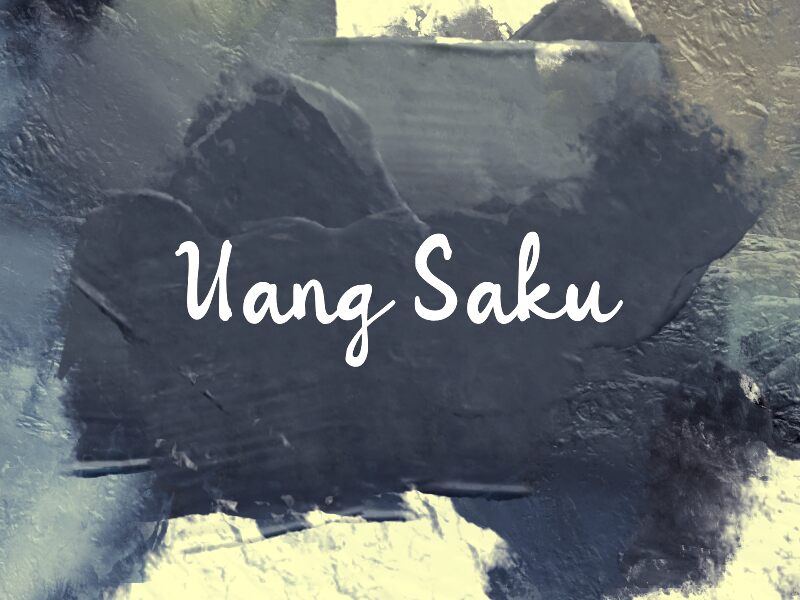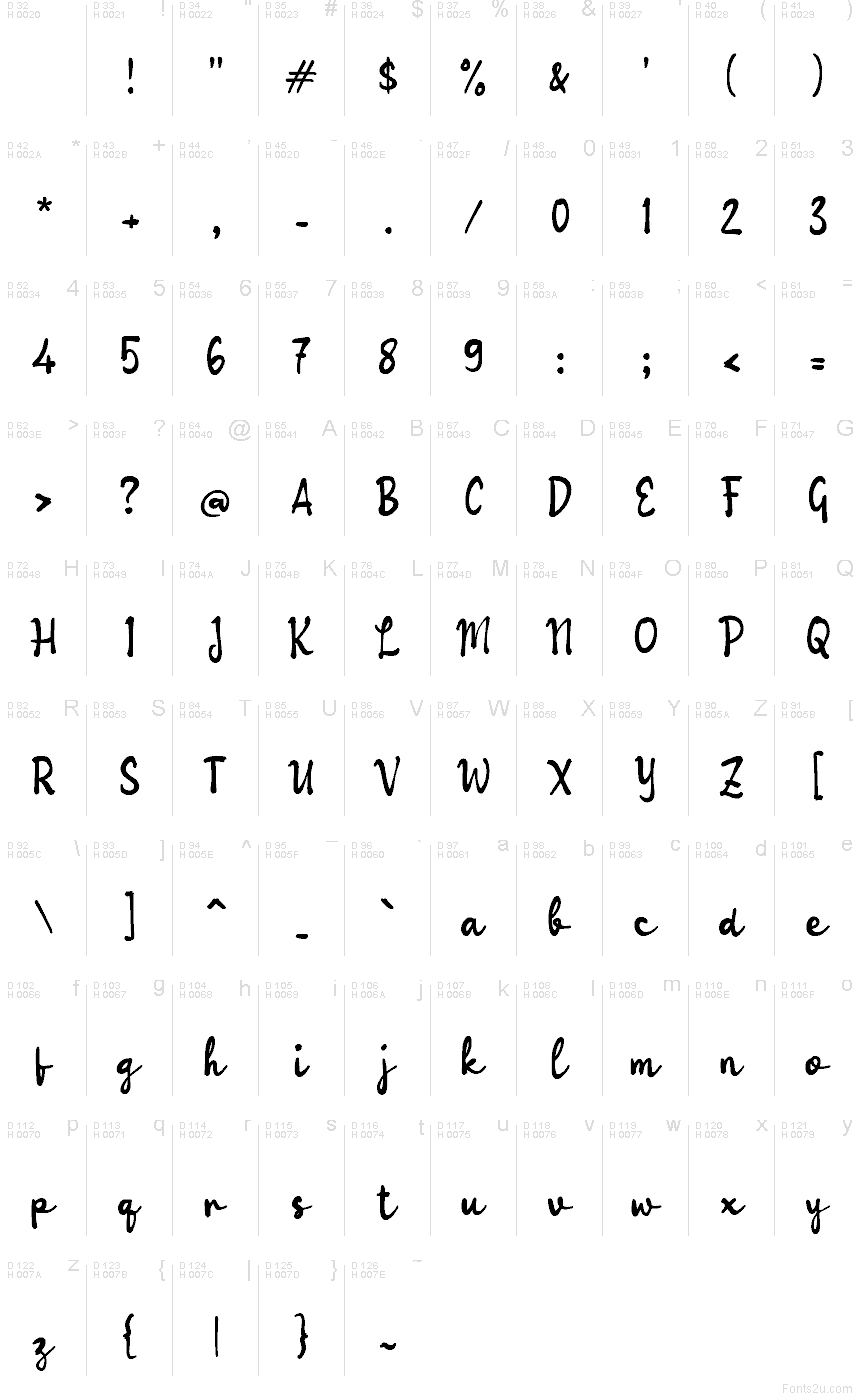
Uang Saku
Uang Saku di Wep è un font brush script scritto a mano, gratuito e dallo stile vivace e naturale. Le lettere sembrano dipinte con un gesto sciolto: curve rotonde, tratti corposi e una linea di base irregolare conferiscono al carattere un mood informale, simile a un appunto scritto a mano, lontano dal rigore della calligrafia tradizionale.
Si adatta perfettamente al branding di caffetterie, al packaging di snack, ai titoli di locandine, alle card social o alla grafica per merchandising, dove un tocco umano risulta più efficace di una lettera troppo perfetta. È ideale per titoli brevi, slogan e logotipi, poiché le curve sinuose e le aperture ampie lasciano respirare le parole.